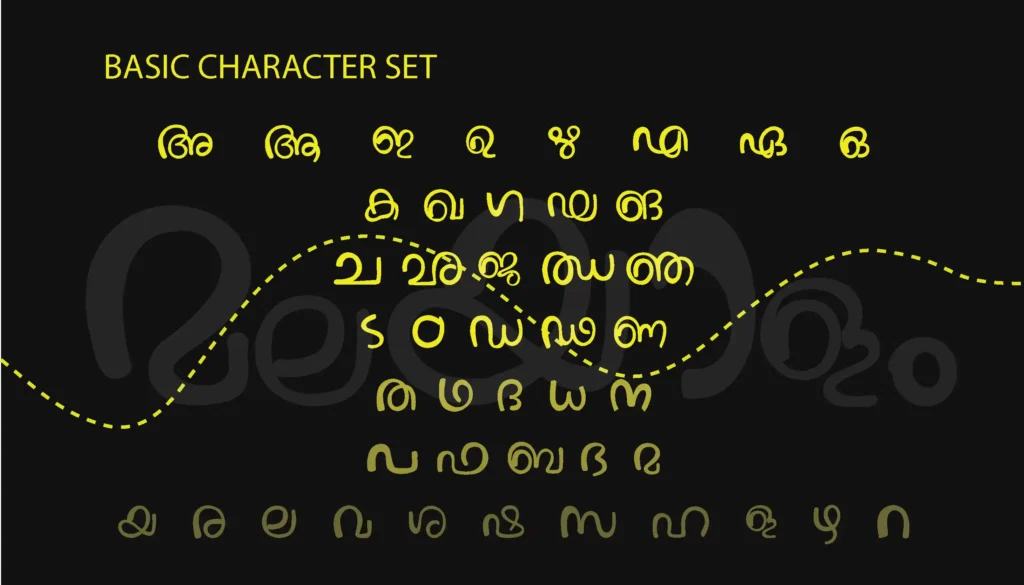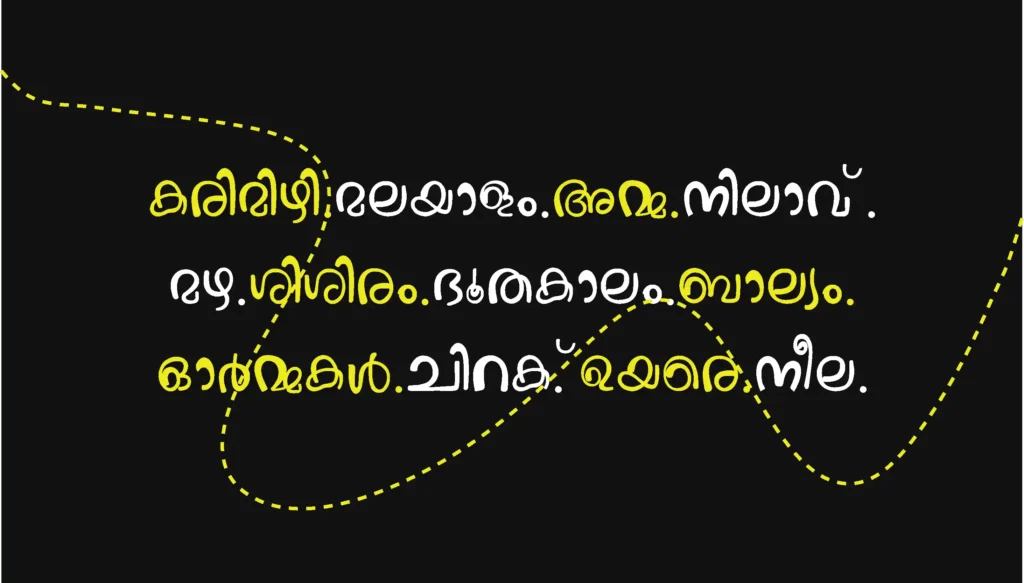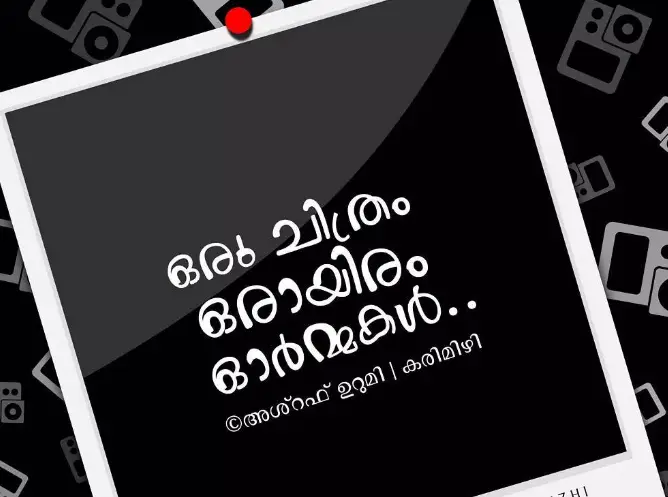
മലയാളത്തിന് വ്യത്യസ്തമായൊരു ഫോണ്ട് സമ്മാനിക്കുകയാണ് ഡിസൈനർ ആയ വിദ്യപ്രിയ. തൻ്റെ സ്വന്തം കൈയക്ഷര ശൈലിയിൽ തന്നെ എഴുതി തയ്യാറാക്കിയിരിക്കുന്ന ഈ ഫോണ്ട് FML -സീരീസിലുള്ളത് ആണ്. ടൈറ്റിൽ ഡിസൈനിനു വേണ്ടി കൂടുതലായും ഉപയോഗിക്കാൻ തരത്തിൽ ആണ് ഈ ഫോണ്ട് ഡിസൈൻ ചെയ്തിരിക്കുന്നത്. കൈയക്ഷര രീതിയും മനോഹരവുമായ ഒരു ടൈപ്പ്ഫേസാണ് കരിമിഴി-രണ്ടുവര എന്നത്.
Karimizhi-Randuvara is a handwritten, soft, and elegant typeface that can be used in various ways to amplify your projects.